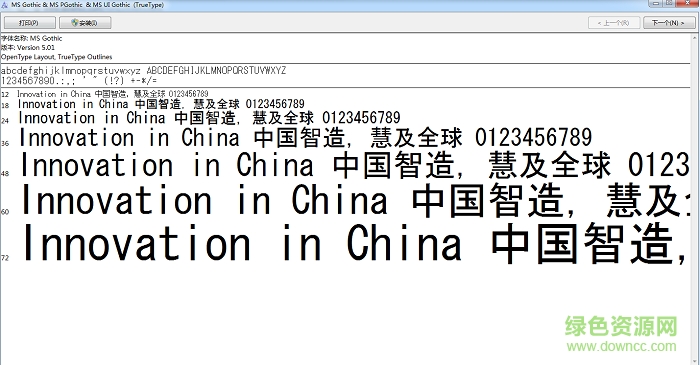
ms pゴシック是什么字體?ms pゴシック什么意思?ms pゴシック字體又叫ms pgothic,是一款游戲中常見的日文黑體字體,結構嚴密,筆畫粗細一致,易于閱讀,需要的朋友快來下載吧!
“黑體”是一類字體的總稱,有很多字體都屬于這個范疇,特點是沒有襯線裝飾,筆劃粗壯有力,撇捺等筆畫不尖,由于其醒目的特點,常用于標題,導語,標志等等。